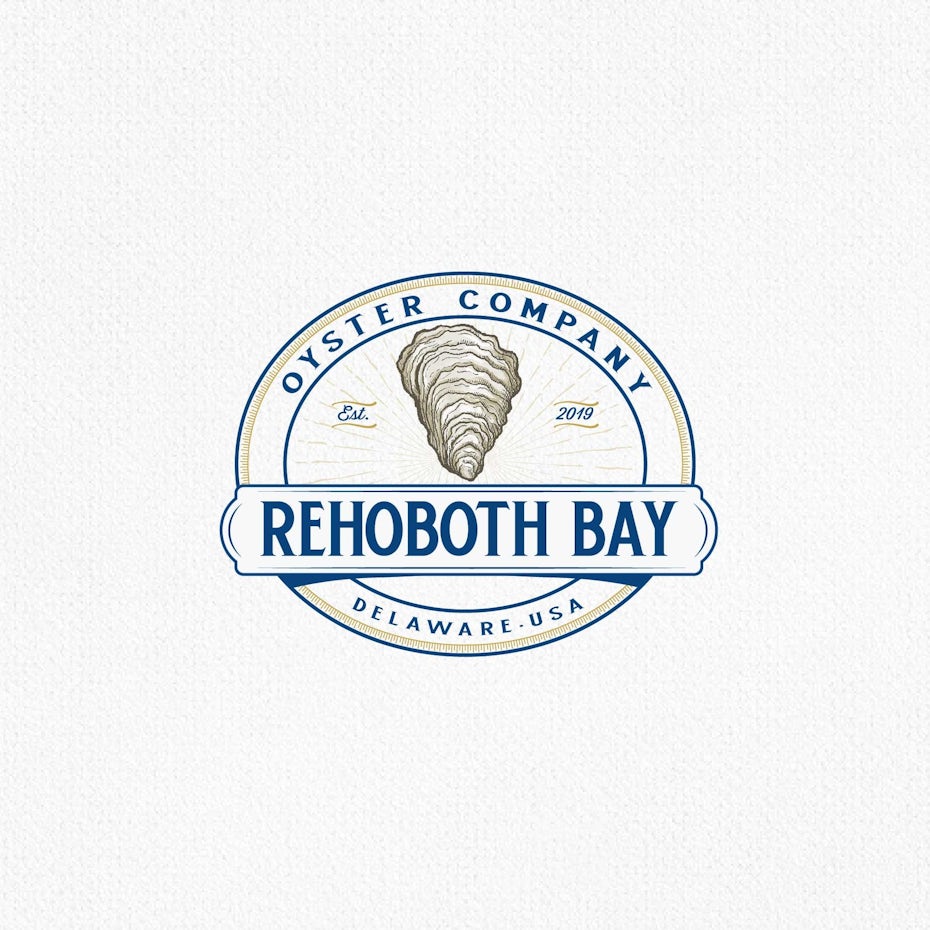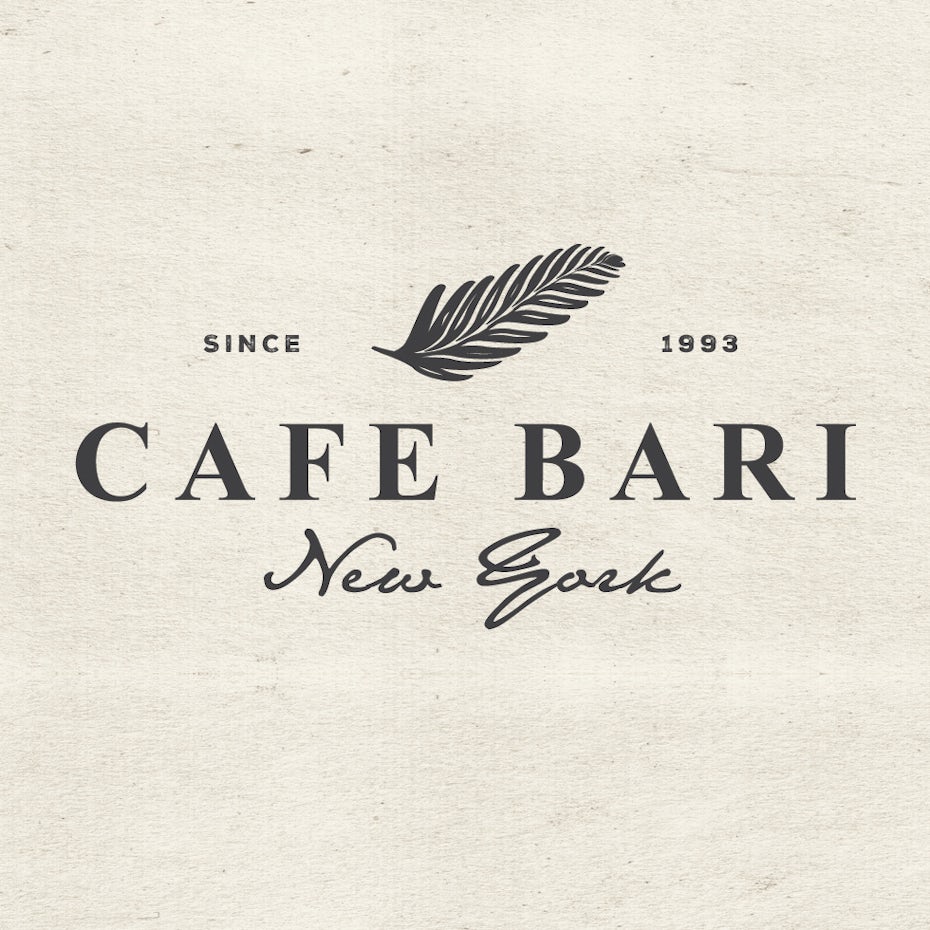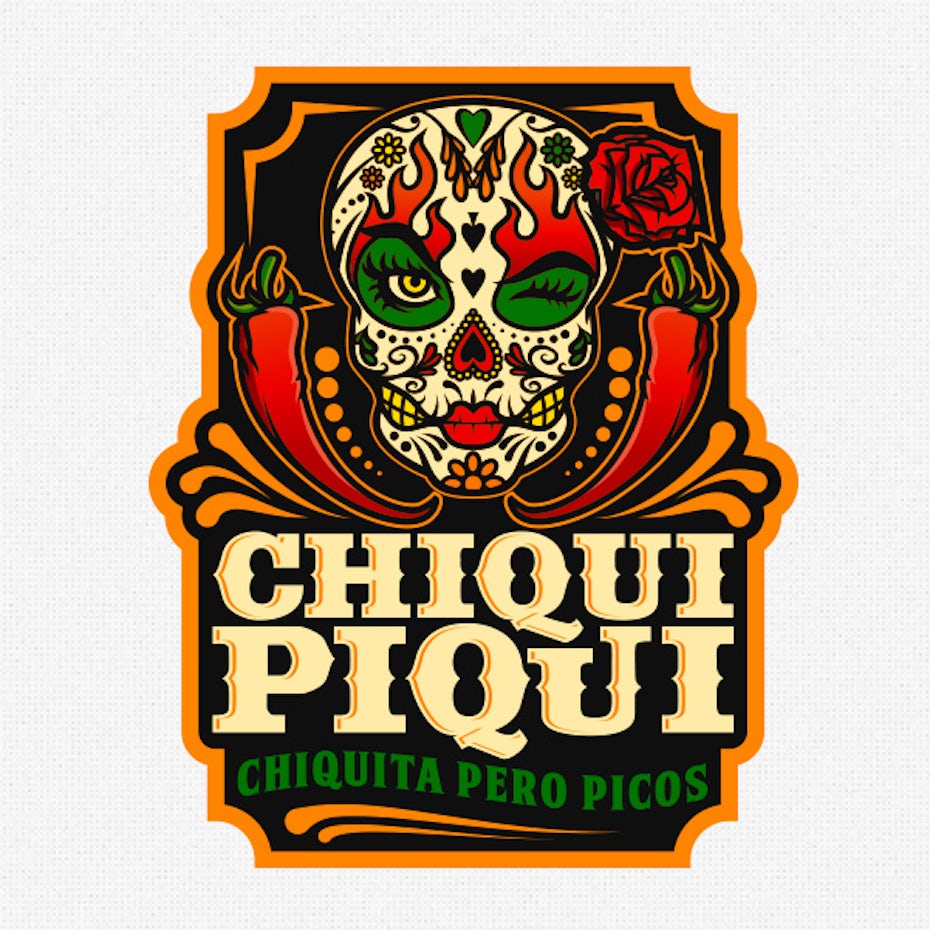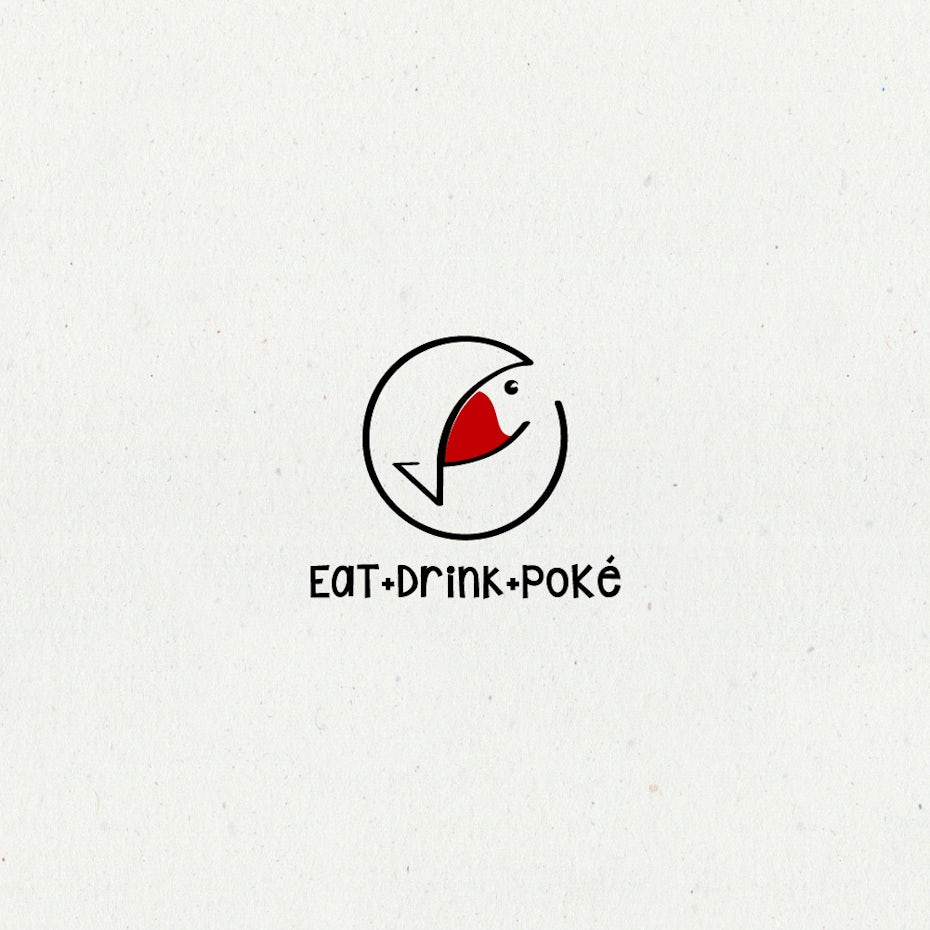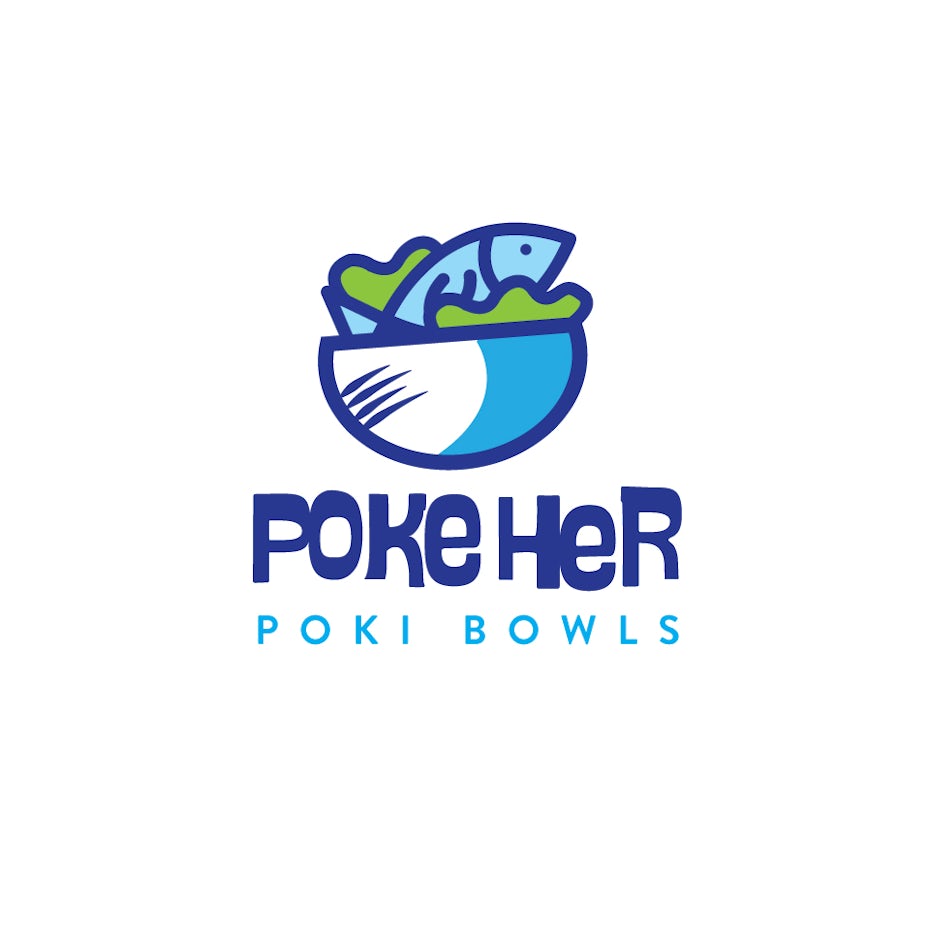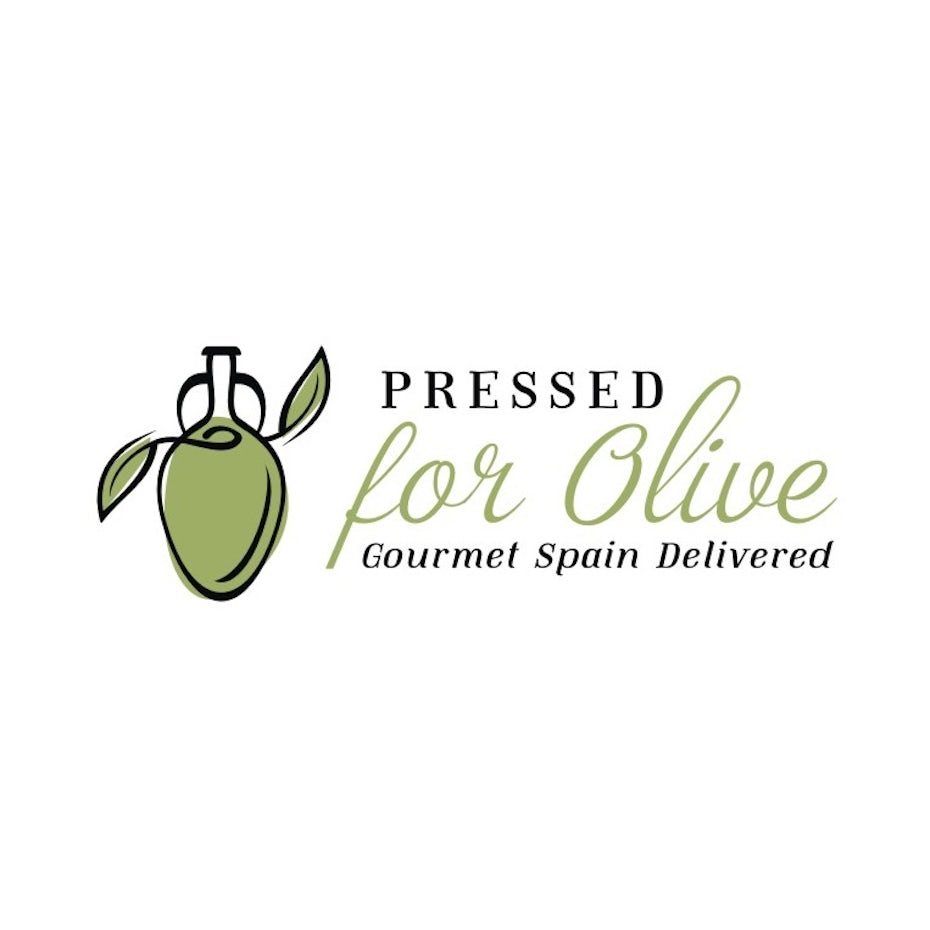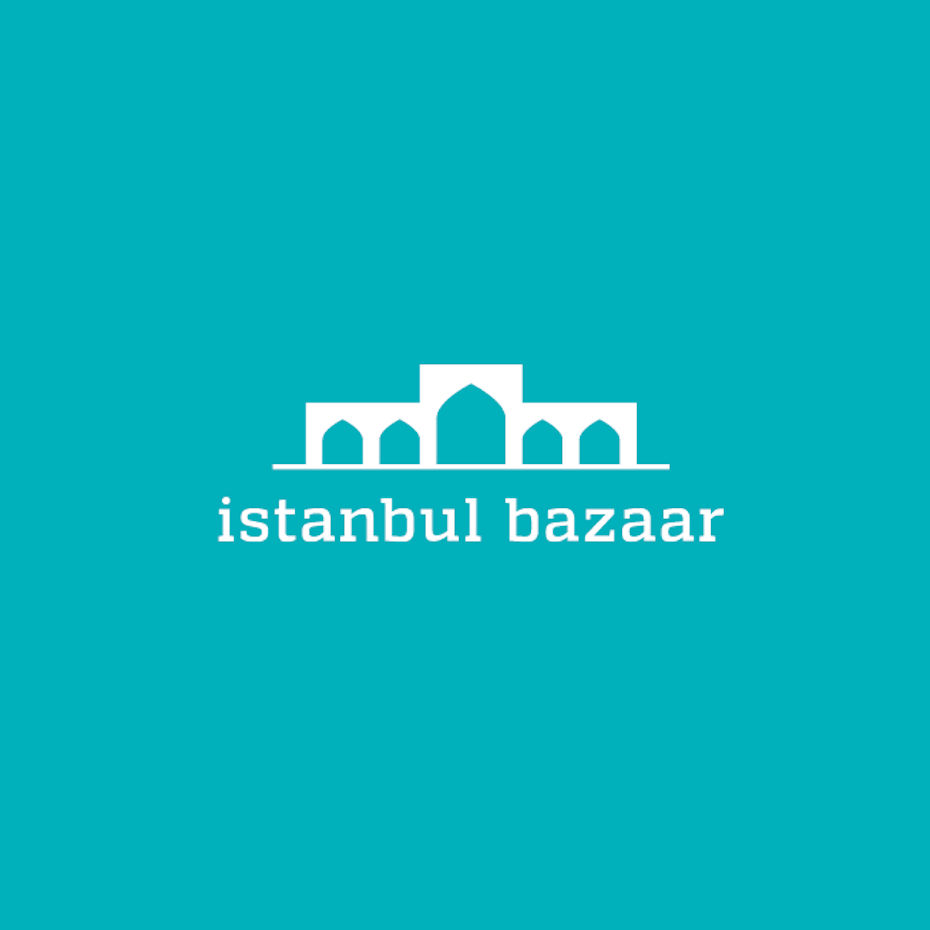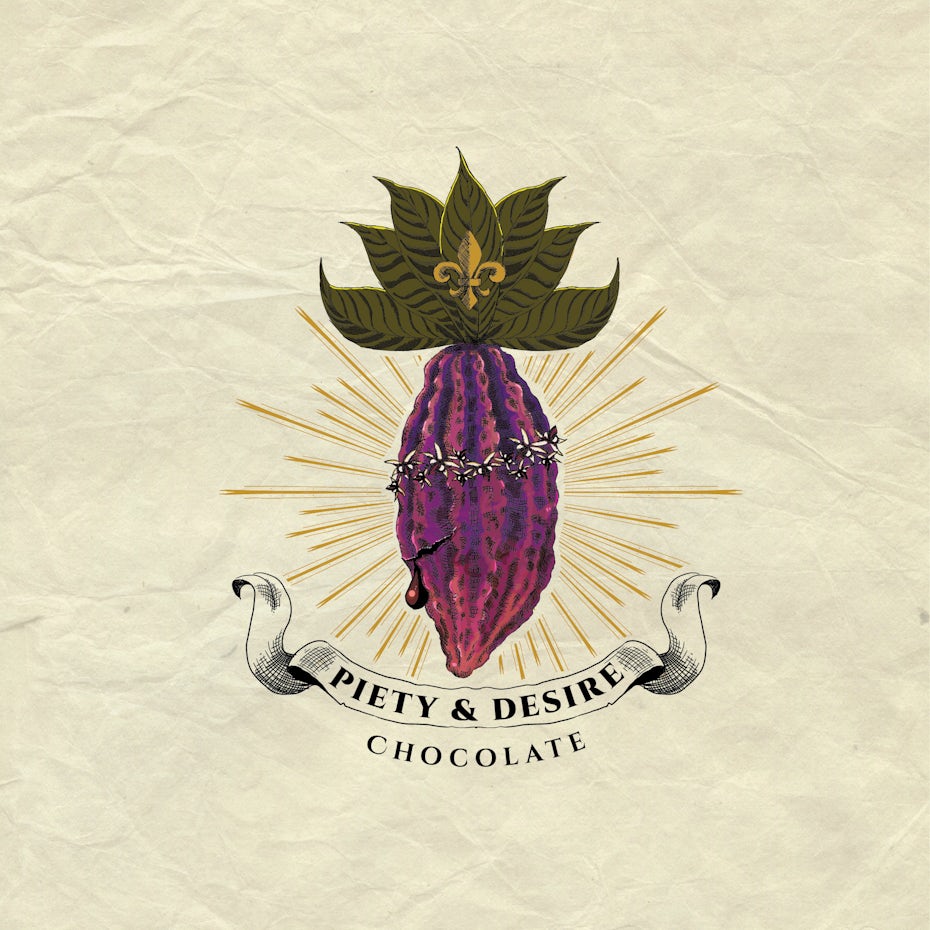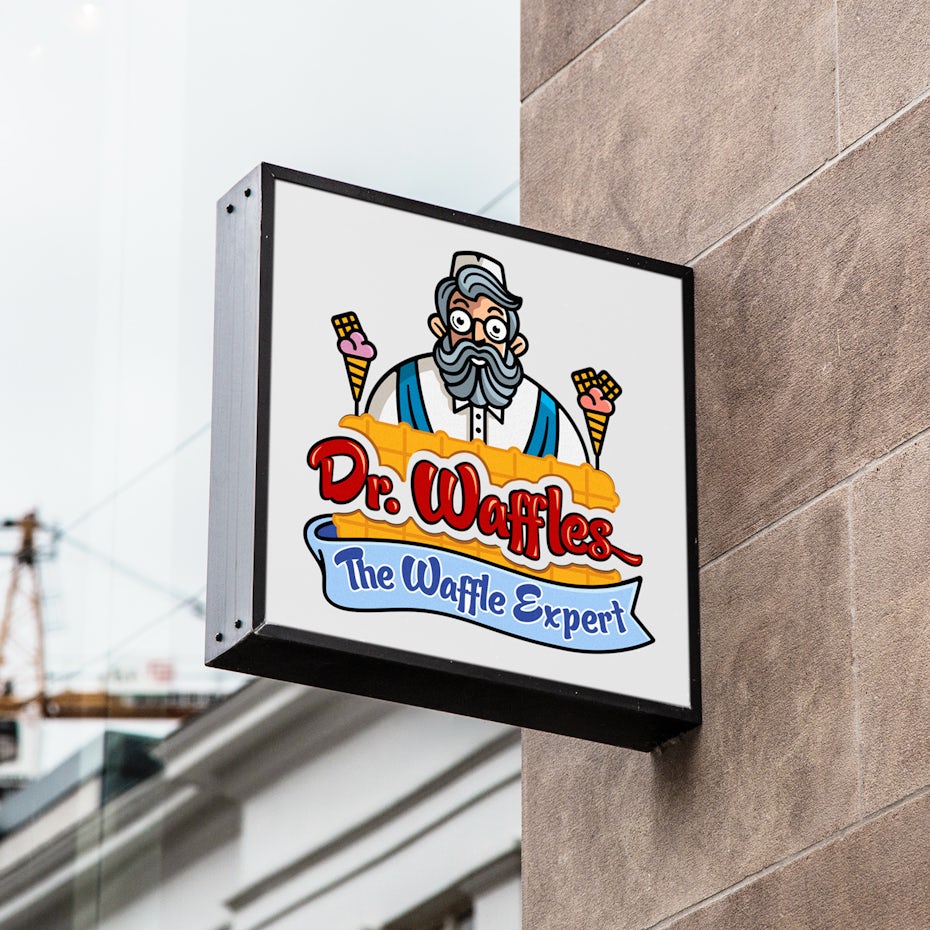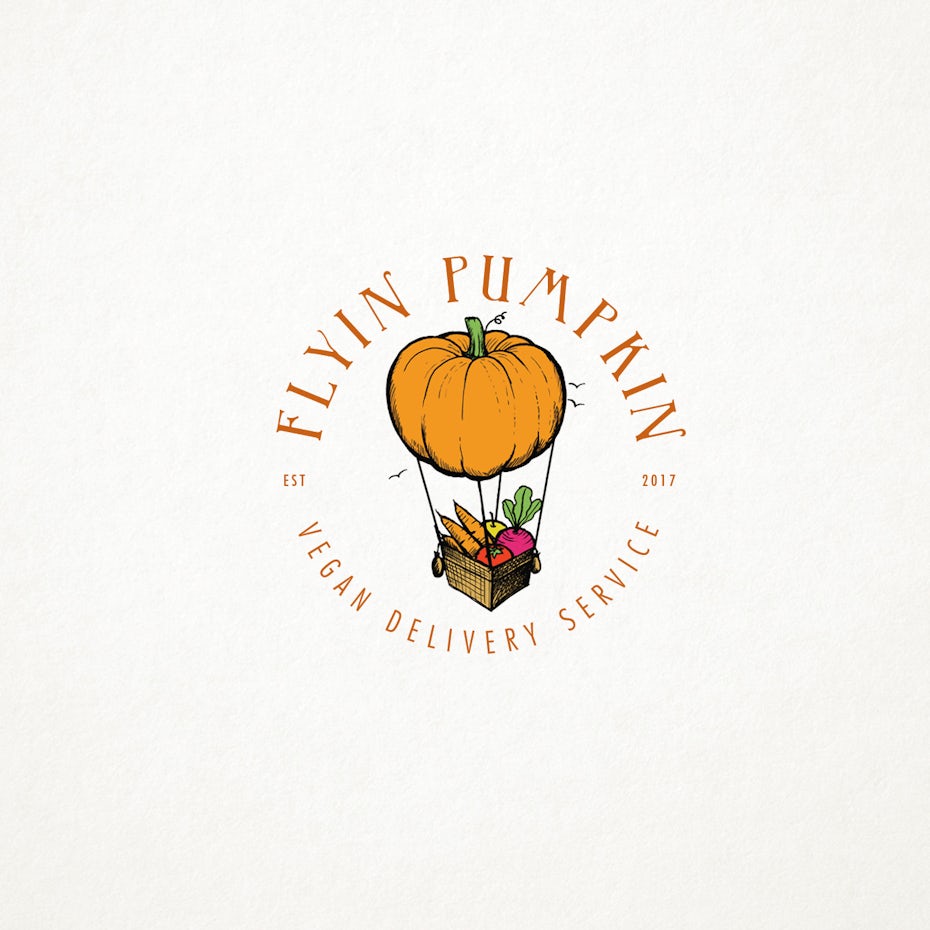
42个美味的食物标识分享,让你口水直流!
我们每天都与食品标识互动。我们从冰箱里拿了一箱牛奶,沿着一条路经过熟食店和餐馆,也许我们还会跑到杂货店买点快餐。我们一直在评估品牌为我们提供的食物选择 - 食物标志在做出这些选择方面起着重要作用。
那些最能吸引我们的,并且以最好的方式形象地传达他们的品牌形象的人,通常是顾客和我们在一起的人。标志设计是品牌形象的表达,告诉潜在客户你是谁,你代表什么,为什么他们应该把钱花在你提供的美味佳肴上的重要机会。
不同的食物标识的集合
在创建食品标识时,仅仅想出一些引人注目的东西是不够的。成功的食品标志设计通过吸引顾客的思想,胃和购买习惯。在这里,我们收集了一些美味的食品标识。
什么是好的食物标志?
在设计食品标识时,你需要密切关注食品行业的特点和现实。对于初学者来说,标志应该看起来很美味并且有足够的吸引力。无论你的产品是甜腻的点心还是健康的零食,你的标志都需要吸引顾客的味蕾。
奶酪标志
最重要的是,你的标志也需要看起来值得信赖,因为在一天结束时,人们需要相信以将你的产品放入口中。
这就是为什么选择一个看起来很专业且经过深思熟虑的标志至关重要的原因。没有太多思考或技巧的设计很容易识别,并会给客户留下负面印象。
还有在拥挤的食品行业中脱颖而出的问题。在我们这个时代,食品品牌的多样性不再是一个问题。一旦某些东西变得流行,其他品牌就会开始生产,新品牌也会出现。脱颖而出是棘手的:你需要在竞争对手中适当地说出该产品的共同语言,但要有足够的细微差别,以你独特卖点吸引顾客。
例如,牛奶替代品是一种相对较新的趋势,什么会让你脱颖而出?你的品牌更实惠吗?它更美味或更自然吗?如果它更美味,你可能想要一个更多颜色的标志,这是有趣和明亮的。如果它很自然,你可能希望它看起来更加手工制作,具有大地色调和自然图像。
食物标识的惊人创意
沙拉吧标志
“食品”是一个非常广泛的类别,涵盖更广泛的品牌。要创建自己独特的标志,需要使用你想要强调品牌的特定方面。看看这些食品标志样式,以更好地了解你想要传达的食品标识以及如何做到这一点。
直奔主题的食品标识
有时候你的明星产品很简单,你会希望直接切入美味点,你可以将产品放在标志中。
想想像汉堡王一样的标志性标志。两个面包将红色和多汁的品牌名称夹在中间。或者是Pringles徽标,芯片是隐身的。此类标志适用于一个有主要产品的品牌。
下面这些标志充分利用了负空间,使图像与文本紧密放置甚至重叠。它们紧凑,高效且富有创意。根据你的销售情况,你可以把它带到很多方向。并非所有食物都能像Pringles一样受益。主要要求是:显而易见性。
在罐子徽标的沙拉
泡茶标志
Bill Bakes Pizza Baguette标志
旋流冷冻酸奶徽标
Churro标志
开心果朗姆酒蛋白杏仁饼干标志
冰棒品牌标志
熟悉的品味,熟悉的标志
如果你希望标识能够表明连续性和传统性,复古型食品标识是非常适合的。通过创建与记忆相关的设计,你可以利用现有的关系,与客户建立新的,持久的关系。
这些标志采用曲线衬线,柔和和朴实的色调或简单的双色调风格,手绘风格插图和线条阴影。这些标志的设计看起来像代代相传,就像酸面团的起动器一样。
铜水壶面包店的标志
Rehoboth Bay Oyster Company的标志
爆米花徽标
佩恩家庭农场的标志
老Gus格兰诺拉麦片标志
Minnie Jean Cookies标志
Cafe Bari的标志
弗罗斯蒂先生的冰淇淋徽标
响亮自信的食品标识
这些食品标识并不羞于请求你的关注。它们响亮,大胆的吸引着你。
这些标识非常适合小吃品牌,快餐店以及年轻人的食品。他们也可以很好地强调特定的,大胆的味道。这些响亮的食物标志可以是甜的和果味的,或者它们可以是辛辣的。大胆的口味需要大胆的标志。
要使用这些标志,请考虑插图,鲜艳的颜色,更大胆和更丰满的字体,主题和概念通常令人惊讶或不符合预期。这些标志既休闲又有趣 - 就像它们所代表的品牌一样。
果味大胆的标志
饼干和冰淇淋店标志
热带食品卡车标志
华夫饼店标志设计
热狗标志设计
辣酱标志设计
红色餐厅的标志
放在桌子上的食物标识
我们生活在一个很多人都非常关心他们食物的时代。透明度在食品行业中非常重要。在我们交出物品以查看成分之前,需要说足够让我们接触它。同样适合走进杂货店,果汁吧,从服务订购 - 几乎所有的透明度都是关键。
展示构成产品成分的标志在这方面做得非常出色。这些标识通常非常小,线条简洁。它们简单而且不拥挤,或者它们可以是详细和现实的。只要图像保持内聚力并且其所有组件都清晰可辨,字体和颜色就可以向任何方向发展。
这是产品转发品牌,农场到餐桌餐厅,可持续生产的产品,以及一罐橄榄等单一食品的首选标识。
农场到市场的标志
食品标识与详细的成分
素食杏仁奶油酱标志
素食送货服务标志
巧克力标志与可可豆
按下橄榄标志
戳餐厅标志
坚果品牌标志
简约现代的食品标识
无论你是想要改造先前存在的东西还是想要创造新的东西,简约的标志会让你在今天找到方向。想要吸引千禧一代客户群的食品品牌,或者希望品牌拥有现代,酷炫和时尚的个性,可能更喜欢这种类型的商标。
简约现代食品标识包含很少的东西:颜色,图像,文字。重要性是所有相互作用元素之间的空间。这些标识清洁,易读,易于消化。
煎锅食品卡车标志
伊斯坦布尔集市标志
Deja啤酒厂标志
茶店标志
鱼餐厅酒吧标志
牛奶标志
随时随地的饼干
露营餐美食线标志
了解一个标志设计的基础知识
现在你已经了解了不同类型的食品标识,可能仍然不确定哪一种适合你的品牌。以下是标志设计的一些基础知识,以帮助你了解要注意的内容。让我们总结一些关键点:
“最佳标志类型”没有定义,这是因为从某种意义上来说,标志非常的个性化。最成功的标识是其品牌的最佳表达。红色,引人注目和华丽的可口可乐标志适用于该品牌,但它可能不会像一包洋甘菊茶一样成功,有助于平静和抚慰你。
所以在其他任何事情之前,你必须考虑你想成为什么样的品牌 - 你的“ 品牌形象。”你想如何自我介绍并将自己带入这个世界?是休闲品牌还是正规品牌?喜欢冒险还是更传统?这些问题将指导你的设计选择,特别是颜色,形状和字母。
农场食品标志
颜色,形状和字母。每种不同的颜色和形状都表达了不同的情感和理解 - 例如,具有过度黑色回忆复杂性的徽标,具有较少硬边缘的徽标,具有大量圆圈,看起来更平易近人等。这些考虑因素也扩展到字体选择,正式衬线与休闲无衬线,每个代表你品牌标识的另一个细节。
每一个设计决策都是表达品牌的机会。因此,从战略和意识的角度,从头开始建立自己的品牌形象。